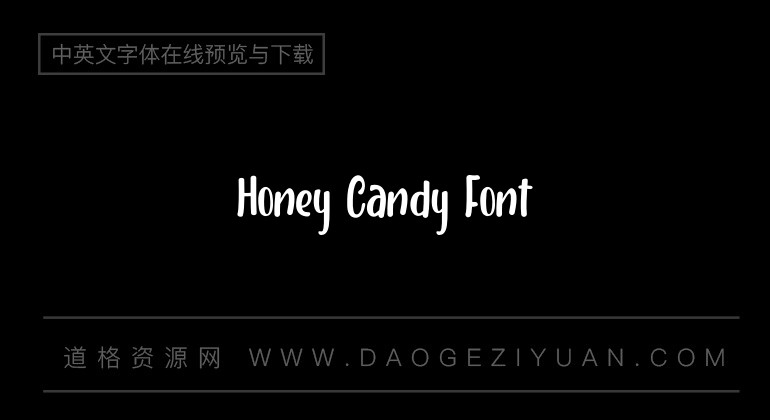
Honey Candy Font 是一款可爱的手写字体,由 Pixel Kitchen 设计。它的特点是类似于手绘风格,字母笔画有一定的不规则性,颜色鲜艳,线条圆润柔和,非常适合用于制作甜品、糖果、卡通等相关的设计和文案。 这个字体包含了大写字母、小写字母、数字和一些常用符号,可以用于标题、标语、海报、名片等设计中。它也可以与其他字体搭配使用,制作出更加丰富多彩的视觉效果。 Honey Candy Font 可以在多个设计软件中使用,例如 Adobe Photoshop、Illustrator、InDesign 等。同时,它也可以在 Windows 和 Mac 操作系统中安装使用。内容介绍
Honey Candy Font是一款非常不错的手写艺术字体,具有很好的视觉感,适合于文化类的宣传设计、商业类品牌的广告和产品包装设计以及个性化文字排版等较多场景。